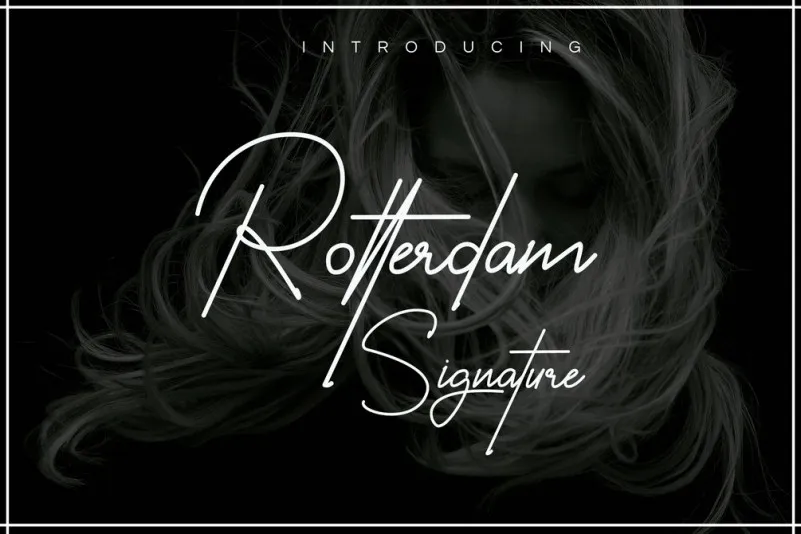
Rotterdam Handwritten Font – Download Grátis
A fonte ‘Rotterdam Handwritten Font’ é uma criação pura resultado do autodesenvolvimento manual. Possui um caráter natural e é uma fonte de script de alta qualidade, com traços suaves e textura simples, que tornam o texto fácil de ler e perfeito para assuntos românticos e apaixonados. Esta elegante fonte de assinatura possui um toque enérgico e bouncingly desenhado. Ela é facilmente legível, o que a torna perfeita tanto para design de marca quanto para designs digitais. Use esta fonte para logotipos, mídias sociais, sites, blogs, Instagrams, cartões de visita, criação de marca e muito mais!